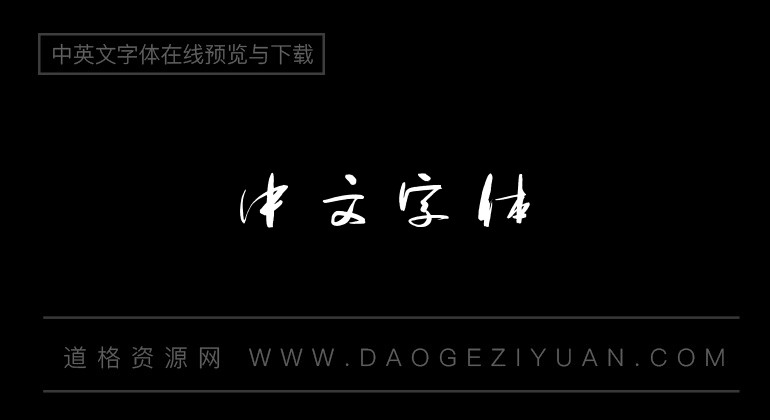
方正字迹-长江行书简体
方正字迹-长江行书简体是一款源自中国传统书法的简体字体,由著名书法家董其昌先生设计,拥有高端的书法美感,结实而流畅的笔画,可以有效地表达出书法的风格,极具艺术性。它的字形有较强的空间感,能够为文字的表达提供更深层次的展示,能够更好地展现出文字的精神内涵。
方正字迹-长江行书简体是一款非常不错的手写艺术字体,具有很好的视觉感,适合于文化类的宣传设计、商业类品牌的广告和产品包装设计以及个性化文字排版等较多场景。